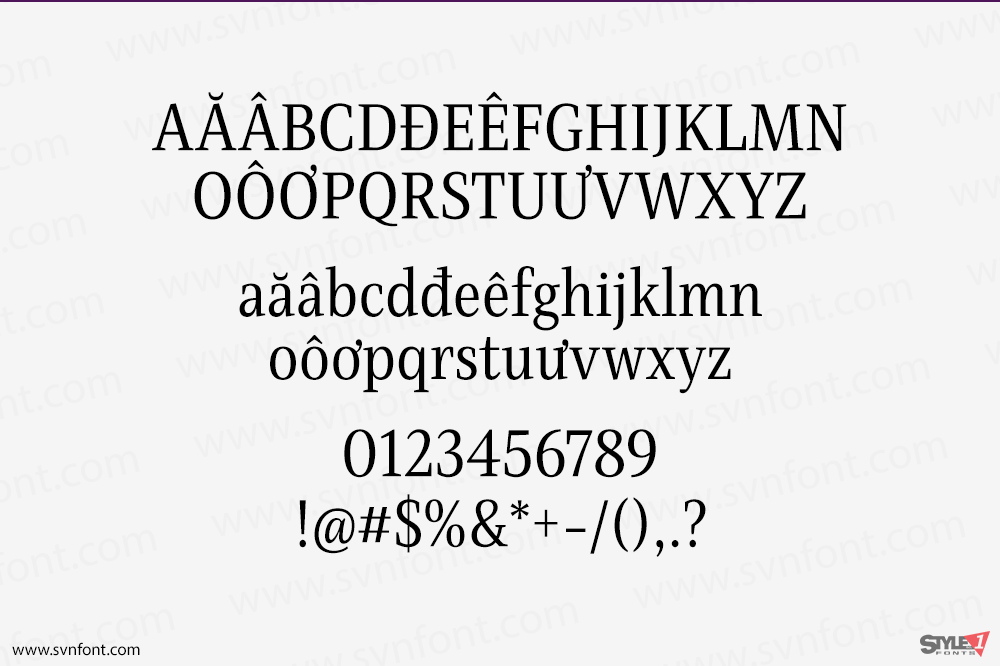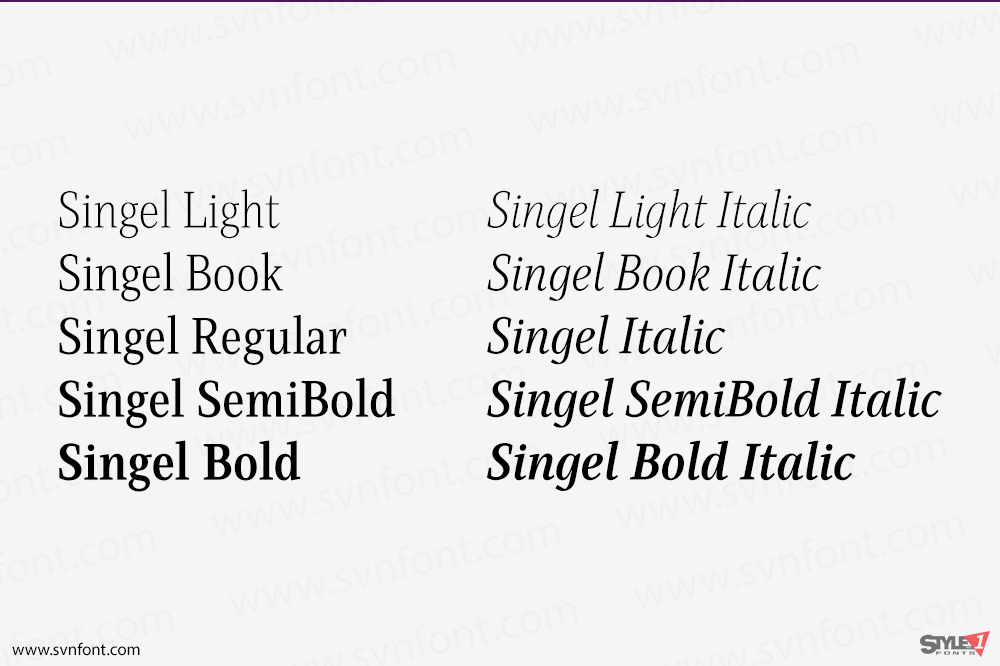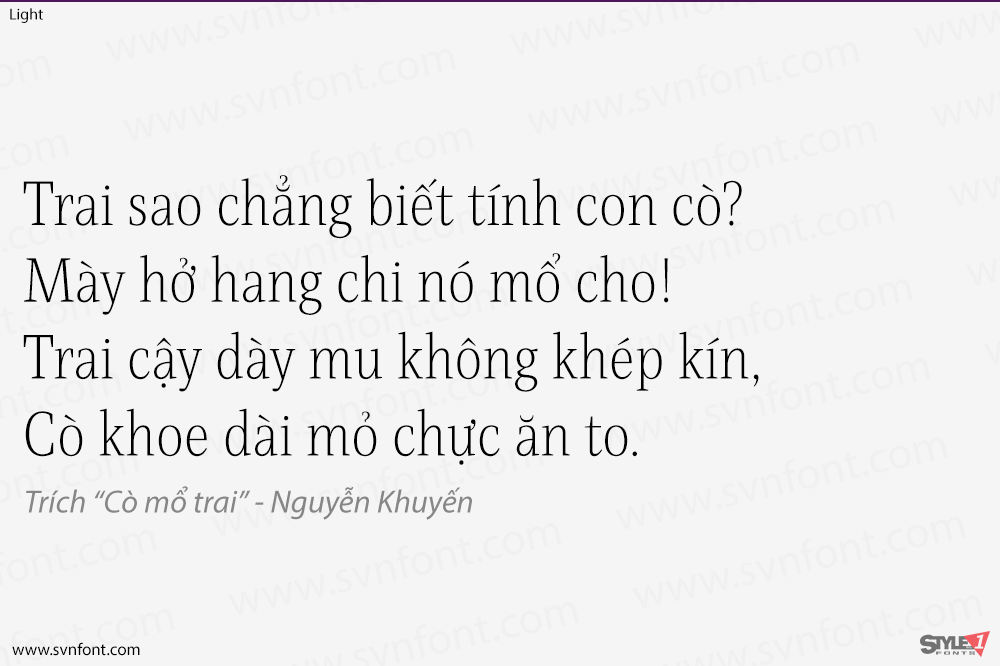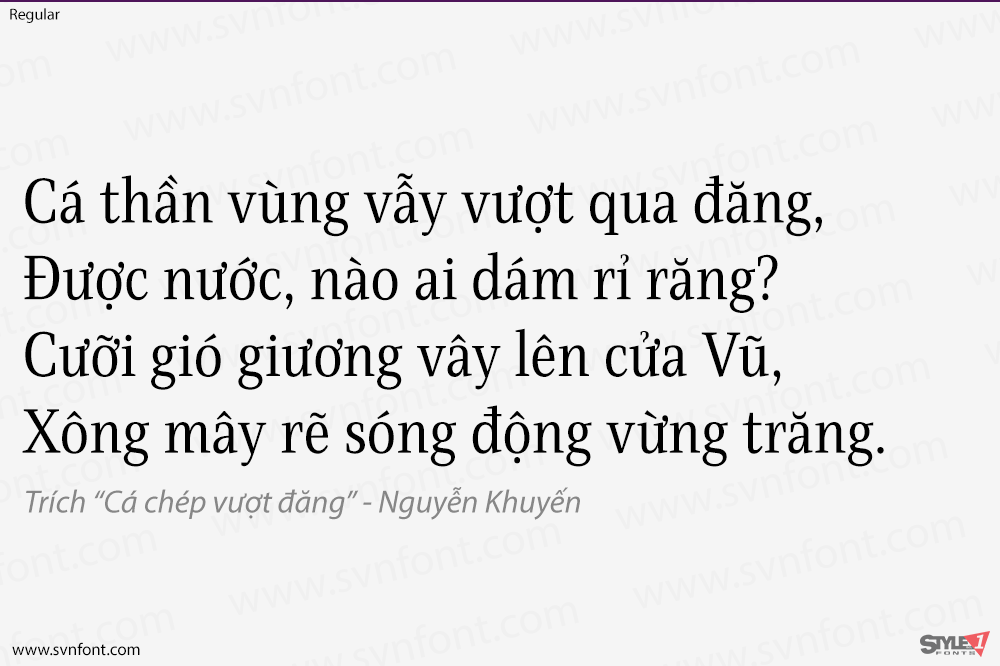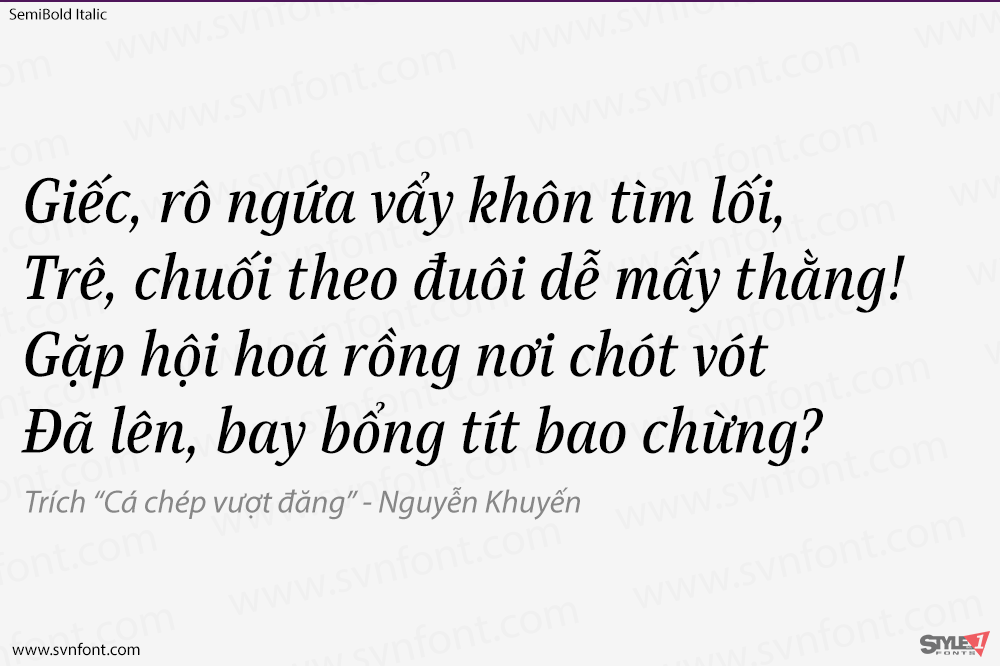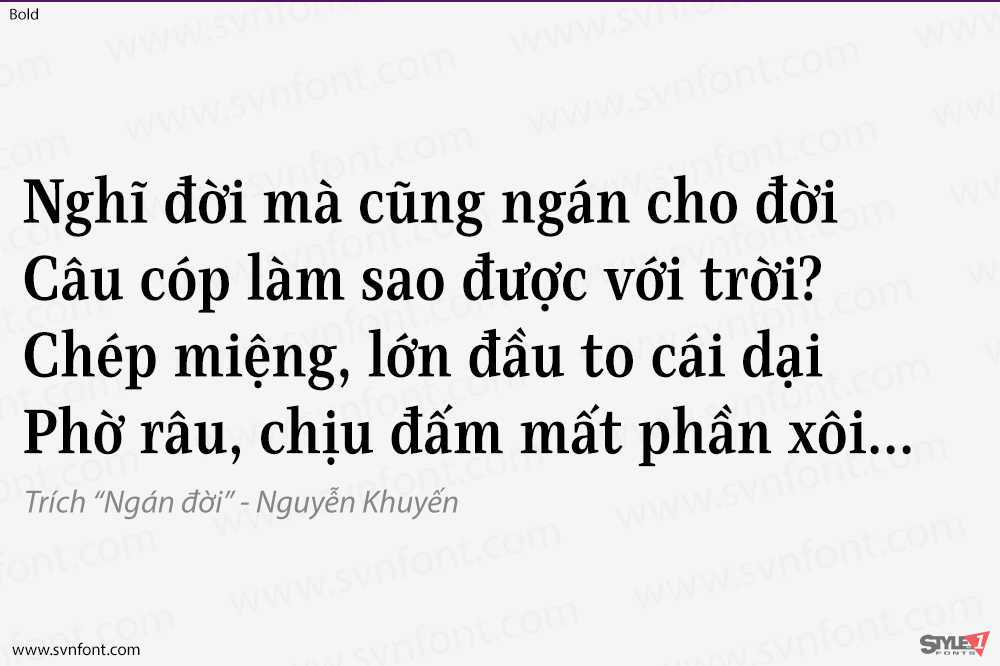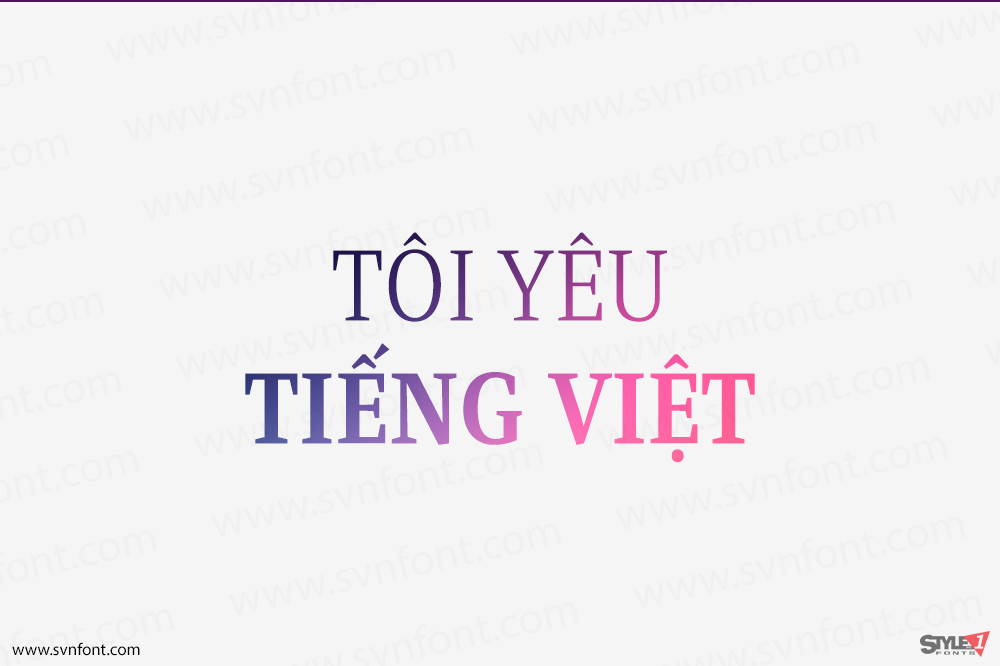
Singel là một font serif tân cổ điển với tỷ lệ hơi cô đọng. Là một bản thể hiện đương đại, kiểu chữ này kết hợp nét điều chỉnh hợp lý với hình dáng thanh lịch và các nét serif sắc nét. Vẻ ngoài lộng lẫy tổng thể của Singel, hoàn chỉnh với bộ chữ hoa nhỏ (Small Capitals) đầy đủ và kiểu chữ nghiêng (italics) đúng chuẩn, làm cho nó hoàn hảo cho bất kỳ thiết kế sang trọng và duyên dáng nào.
Các khía cạnh khác của đặc điểm của nó bao gồm sự nhất quán của 10 kiểu từ Light đến Bold; khả năng bao phủ tiếng Latin mở rộng và Cyrillic với phạm vi hơn 130 ngôn ngữ; chức năng hoàn hảo và hỗ trợ nhiều tính năng OpenType, như bản địa hóa, chữ số dạng bảng (tabular numerals), chỉ số dưới và chỉ số trên (inferiors and superiors), tử số & mẫu số (numerators & denominators), phân số, phân biệt chữ hoa chữ thường (case sensitivity), v.v.
Nhà thiết kế: Nikolay Petroussenko, Jacklina Jekova
Nhà phát hành: Fontfabric